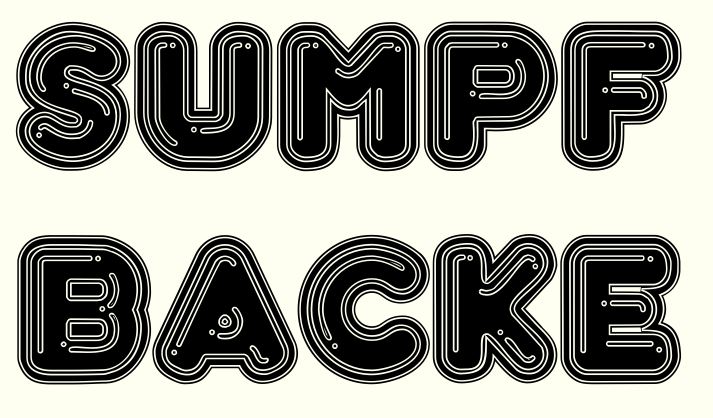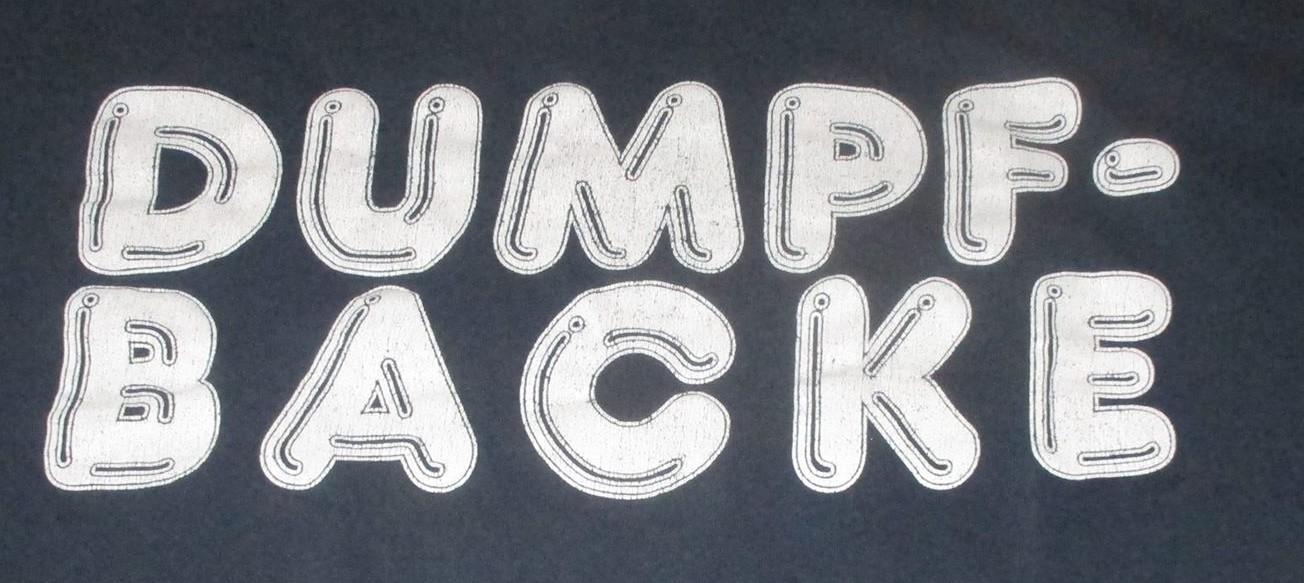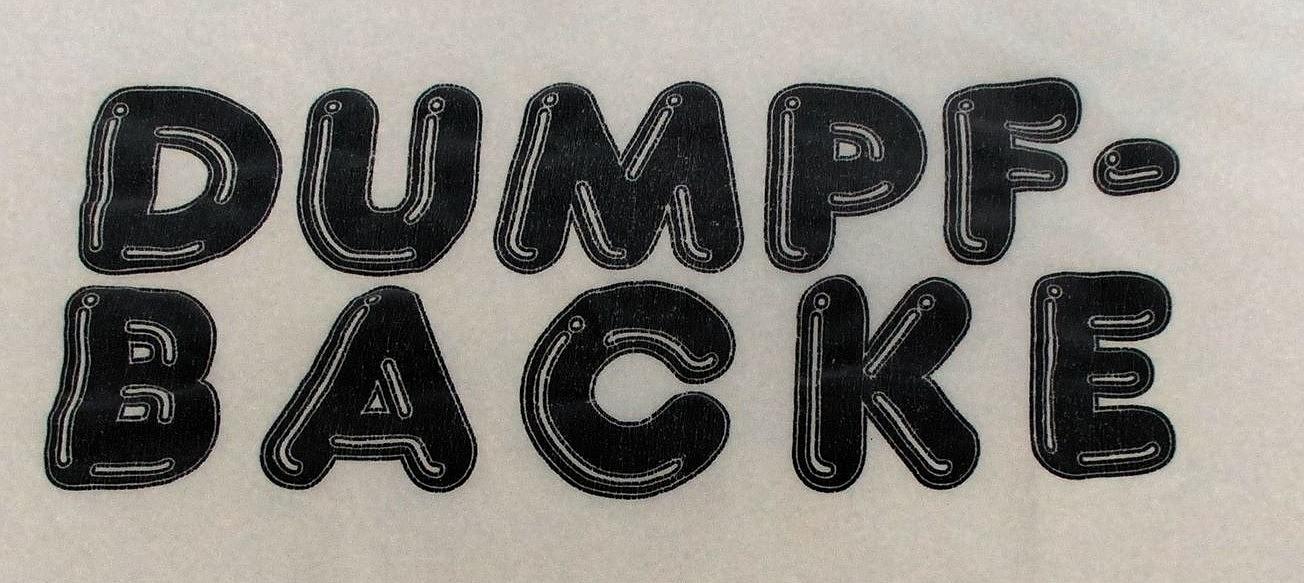
Schriftzug auf einem alten T-Shirt (Dunpfbacke)
eine gute Freundin bekam vor einiger Zeit ein T-Shirt (siehe Bild ) zum Geburtstag. Es war von Anfang an ihr Lieblingsshirt !
Inzwischen ist das Shirt erblasst und ich würde ihr gerne ein Neues selbst bedrucken und schenken.
Habe unglaubliche viele Font-Anbieter abgeklappert, aber nichts außer bubble3d gefunden. Es ist ähnlich, aber nicht das
was ich suche.
Ich würde sagen, das ist die Bubble3D, bei der nur hinterher in einem Grafikprogramm an den Konturen gespielt wird. Hab da ganz schnell mal getestet:
danke Dir, das ist die eine Variante. Hab eben aber Frankfurt gefunden, die kommt dem auch sehr nahe. Aber bei Beiden wurde dran gebastelt.